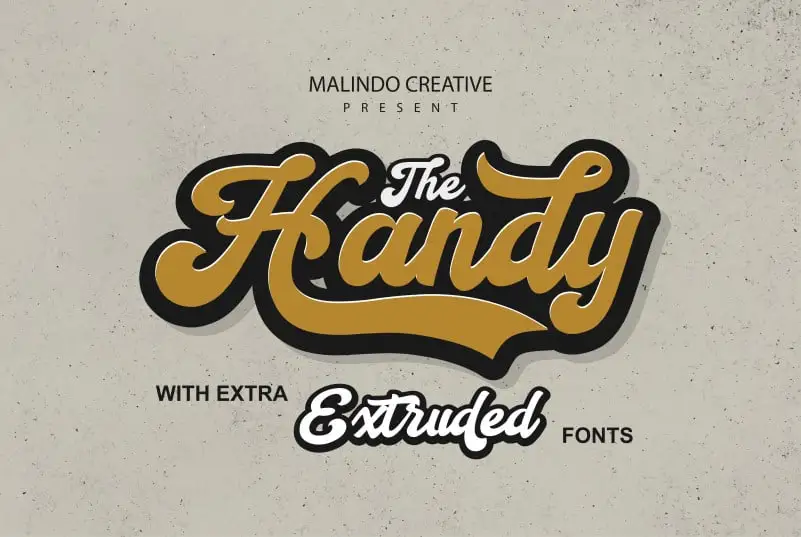
Handy Script Font – Download Grátis
Introduzimos a Handy Script Font, uma maravilhosa fonte na estética retro que vai enriquecer os teus projetos de tipografia. Inspirada nos designs de tipografia clássicos e desejados, essa fonte traz um toque vintage ao seu design. Como parte de um projeto de letra à mão, a Handy Script é perfeita para quem busca uma abordagem moderna do gosto retro que já conquistou o mundo. Ideal tanto para uso em projetos digitais quanto impressos, esta fonte é uma escolha ideal para aqueles que valorizam um toque nostálgico e sofisticado em seus trabalhos de design. Não importa se for um projeto de marketing, ilustração ou qualquer outro tipo, a Handy Script vai adicionar o arco-íris ao seu trabalho. Seja você criador profissional ou hobbyista, essa fonte é uma ótima maneira de trazer um toque diferenciado à sua composição visual, sem precisar de muitos recursos adicionais. Descubra agora mesmo como transformar a forma de seus textos em algo único e inspirador com a Handy Script Font.